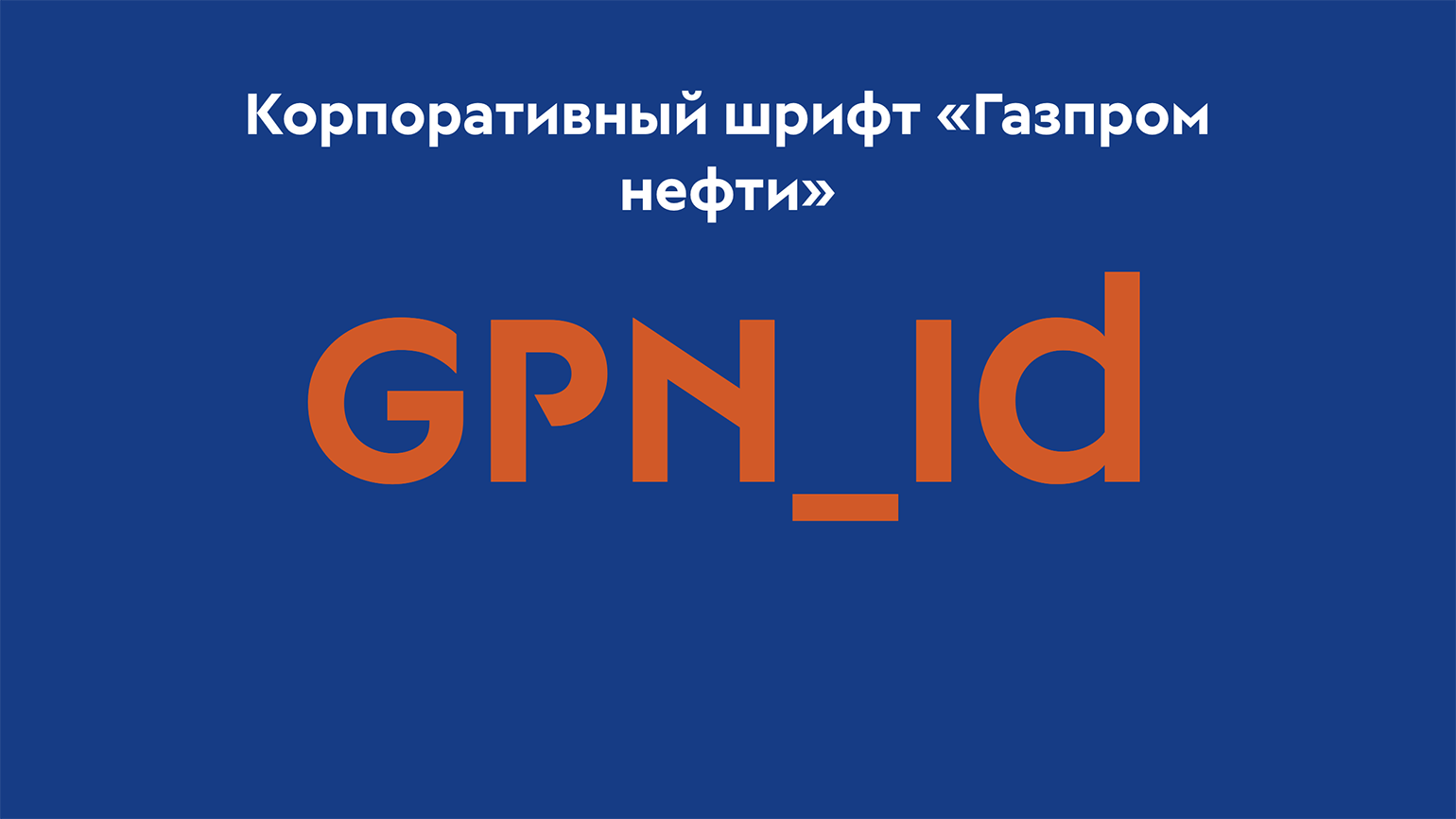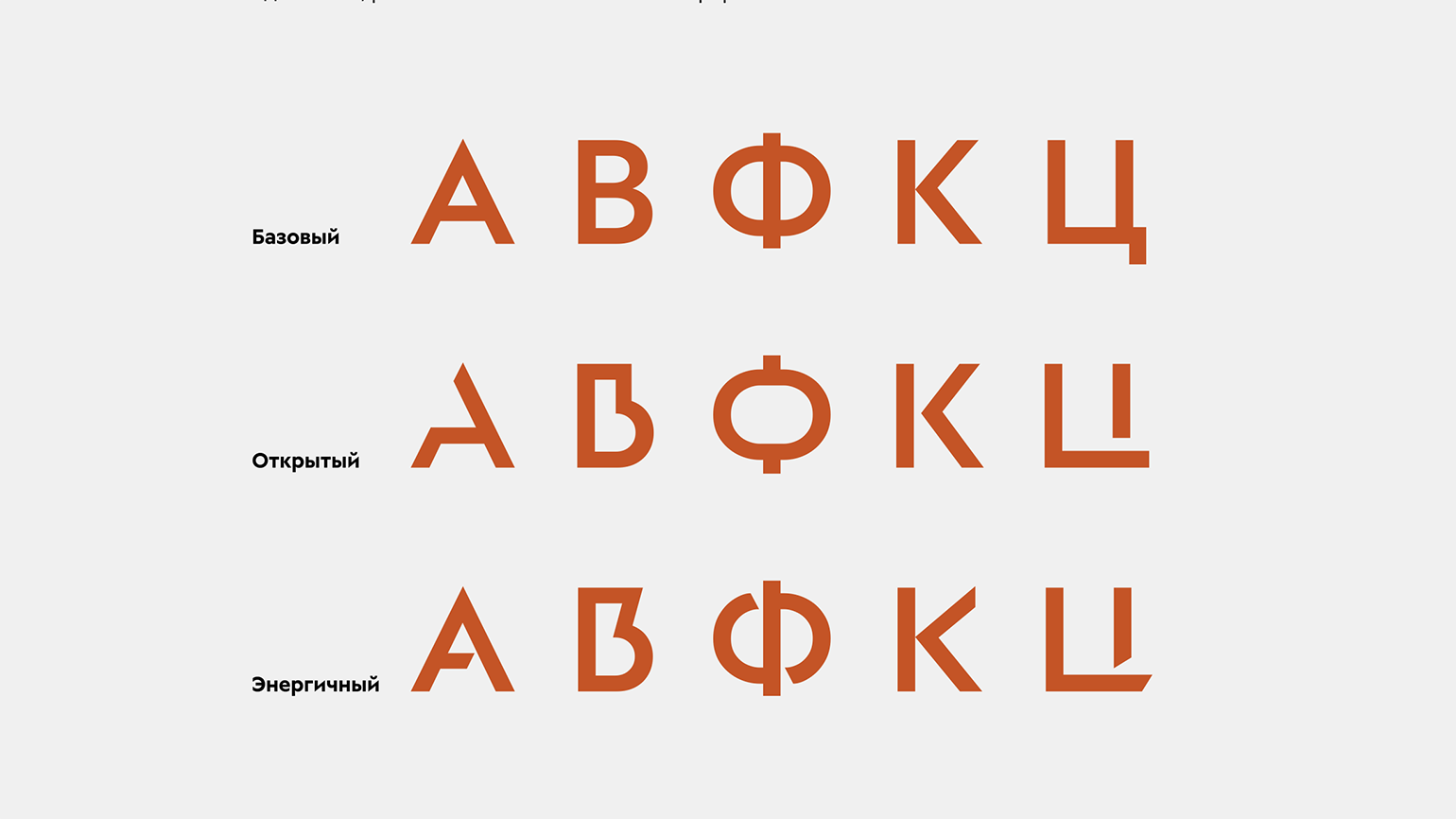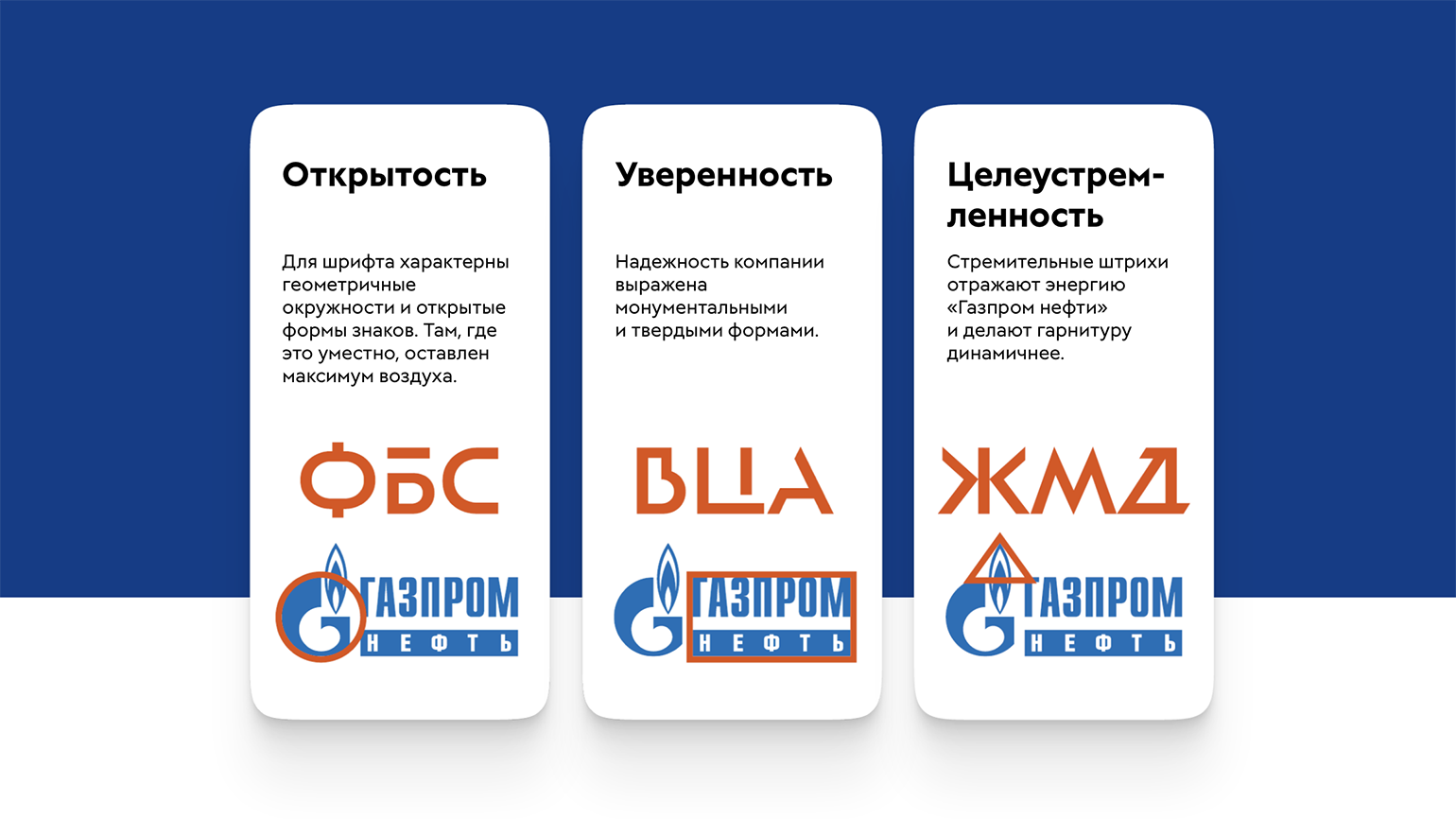
Студия Артемия Лебедева сделала корпоративный шрифт для «Газпром нефти»
Дизайнеры разработали три варианта для разных задач.
Компания «Газпром нефть» пригласила Cтудию Артемия Лебедева, чтобы разработать гарнитуру для шрифтовых логотипов — такую, чтобы можно было использовать для разных новых продуктов и при этом чтобы они все были в едином стиле.
Корпоративный шрифт «Газпром нефть»
Дизайнеры сделали шрифт-конструктор. Он отражает три основные ценности — открытость, уверенность и геометричность. Формы знаков открытые: там, где возможно, оставили максимальные просветы. В то же время они твёрдые и «монументальные» — через это стремятся передать надёжность компании. Резкость штрихов делает шрифт динамичным.
Корпоративный шрифт «Газпром нефть»
Сделали базовую гарнитуру и два акцидентных набора. Все варианты строятся по единой геометрии — там одинаковая ширина знаков, толщина штрихов и степень скругления, различия заключаются лишь в формах символов. Базовая гарнитура самая универсальная и подходит для названий и дескрипторов. В «открытой» гарнитуре увеличены внутрибуквенные просветы. А в «энергичной» гарнитуре больше скосов штрихов и острых углов.
Корпоративный шрифт «Газпром нефть»